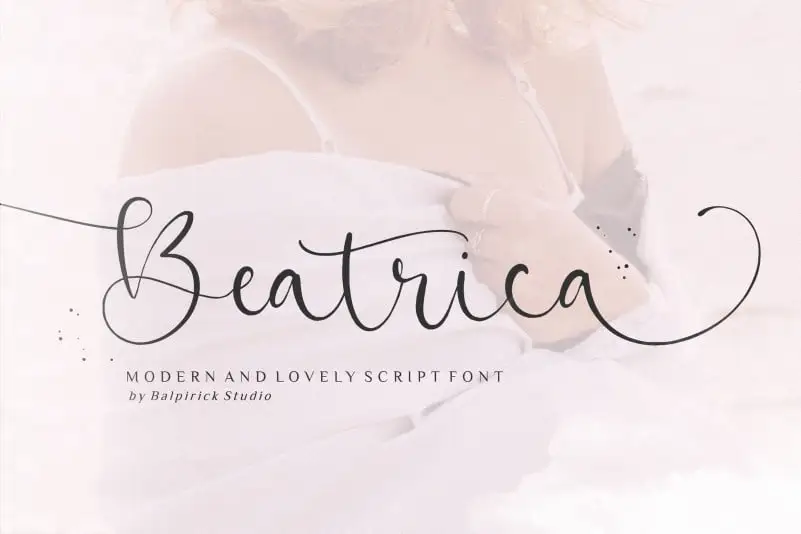
Beatrica Script Font – Fonte Grátis
Beatrica Script Font
A fonte Beatrica Script Font é uma opção perfeita para quem busca um estilo elegante e sofisticado, especialmente adequada para aplicações visuais variadas. Desenvolvida pelo designer balpirick, esta fonte exibe características que podem ser facilmente adaptadas à produção de embalagens de produtos, criação de marca, jornais, redes sociais, desfiles de noivas ou qualquer outra aplicação onde você gostaria de destacar mensagens em cima de fundos. Seja ela uma maneira criativa de adicionar uma nota personalizada a um produto ou um recurso visual memorável para sua campanha publicitária, Beatrica Script Font se destaca pelo seu caráter elegante e fluido, oferecendo um toque especial à qualquer projeto gráfico.